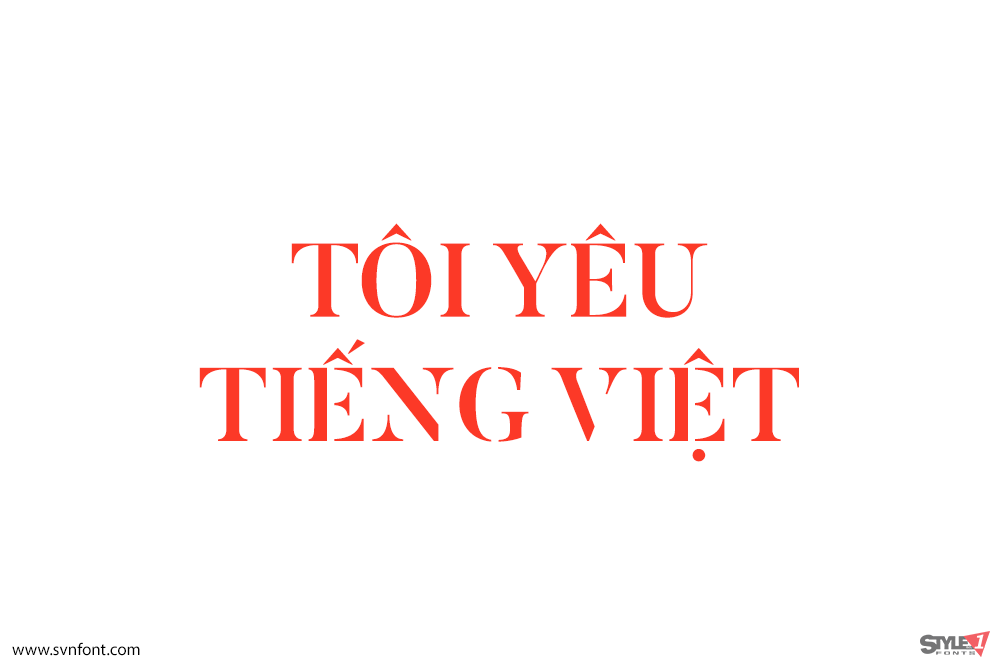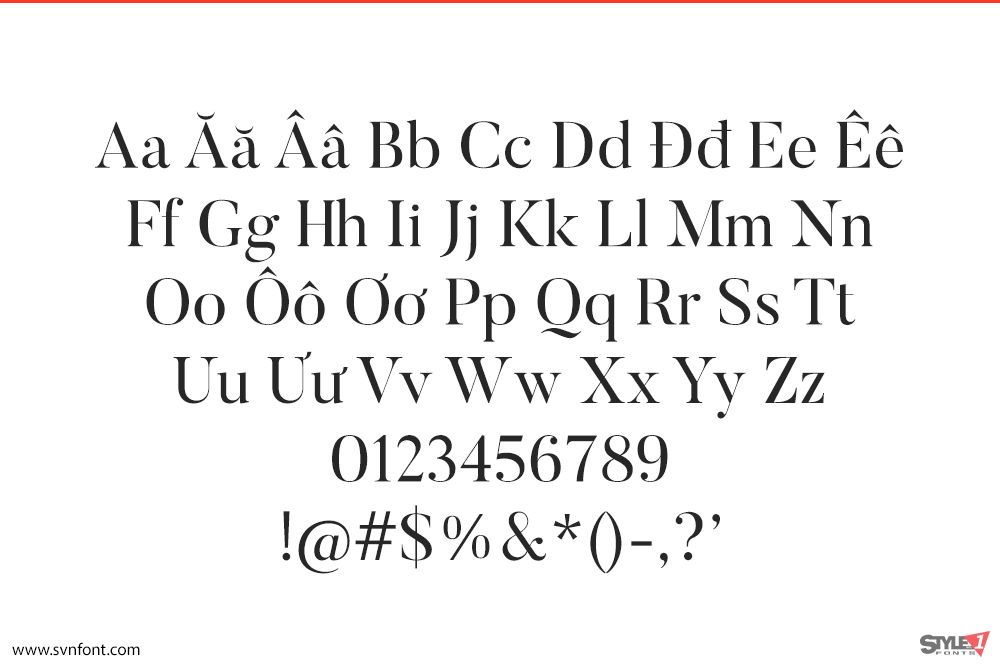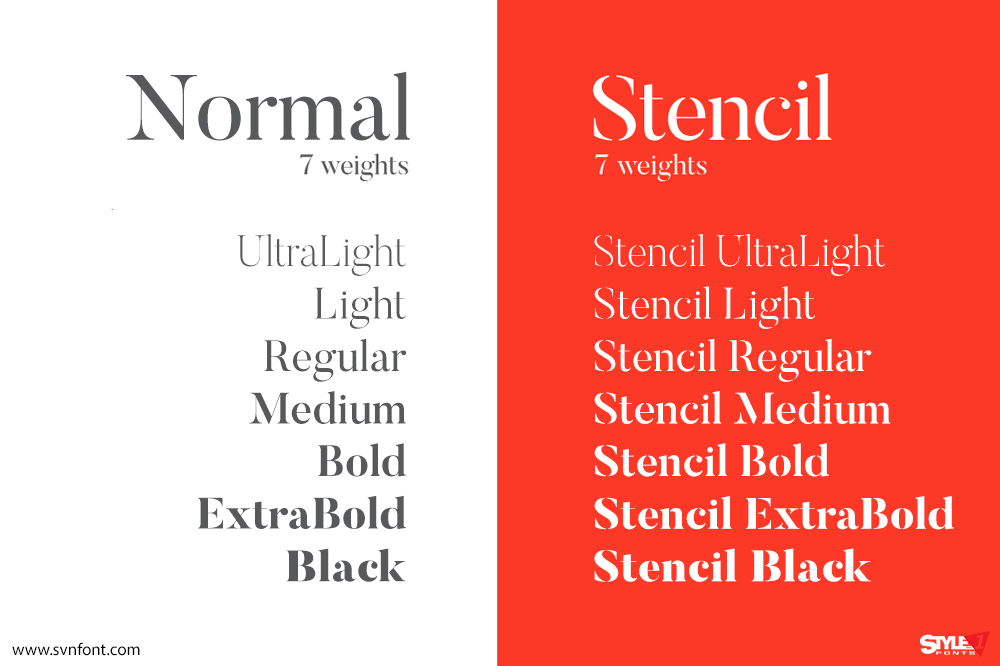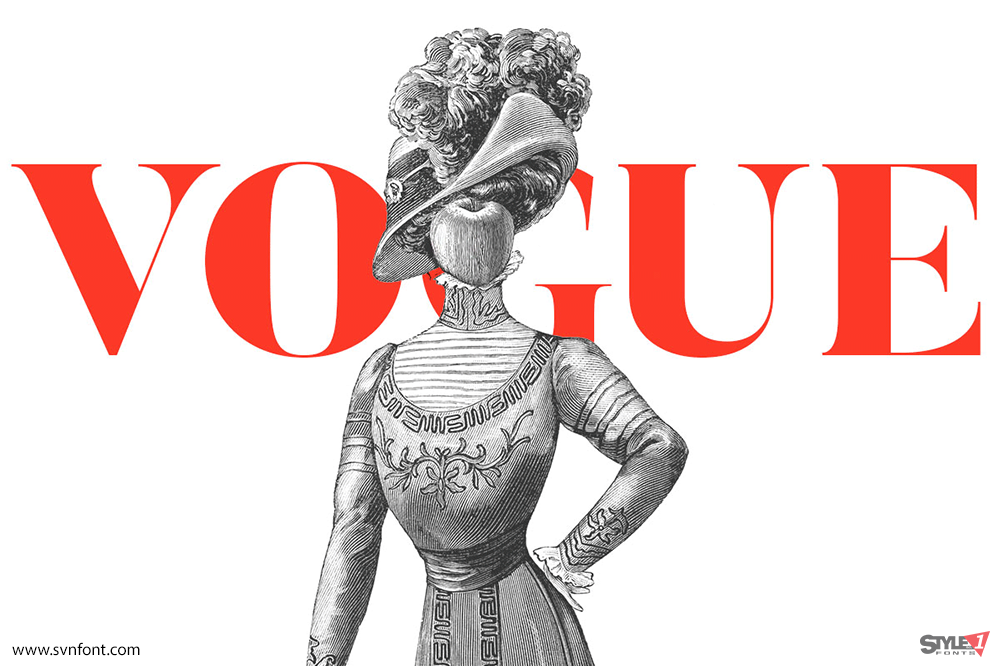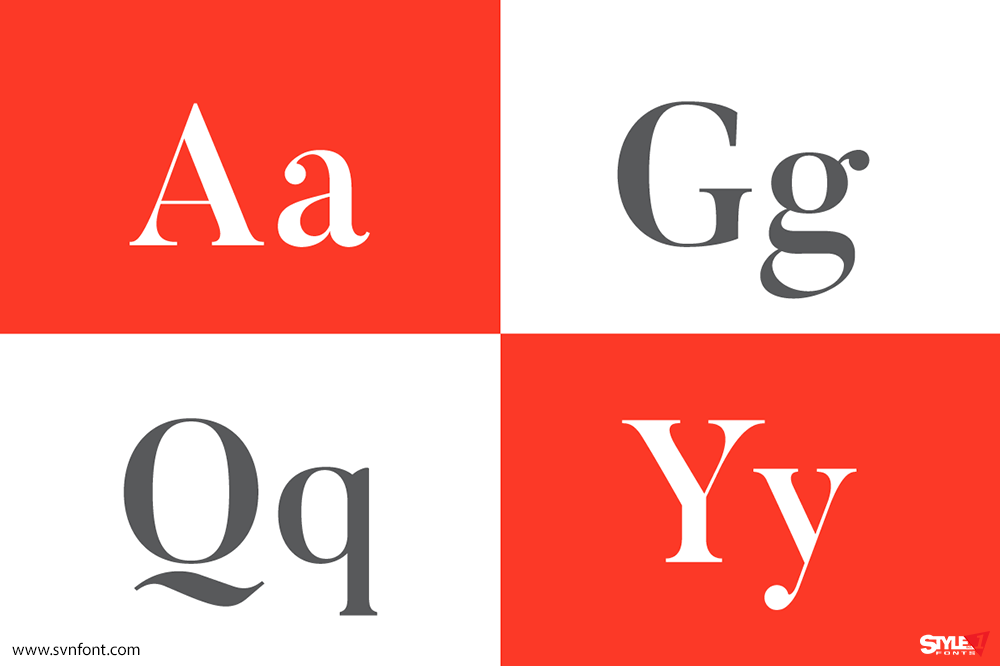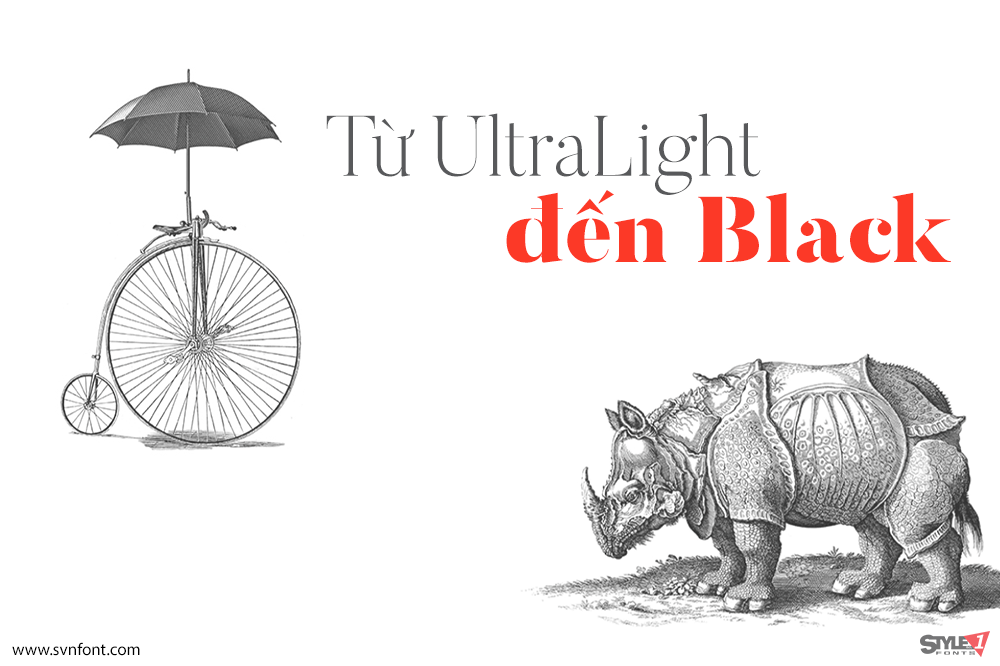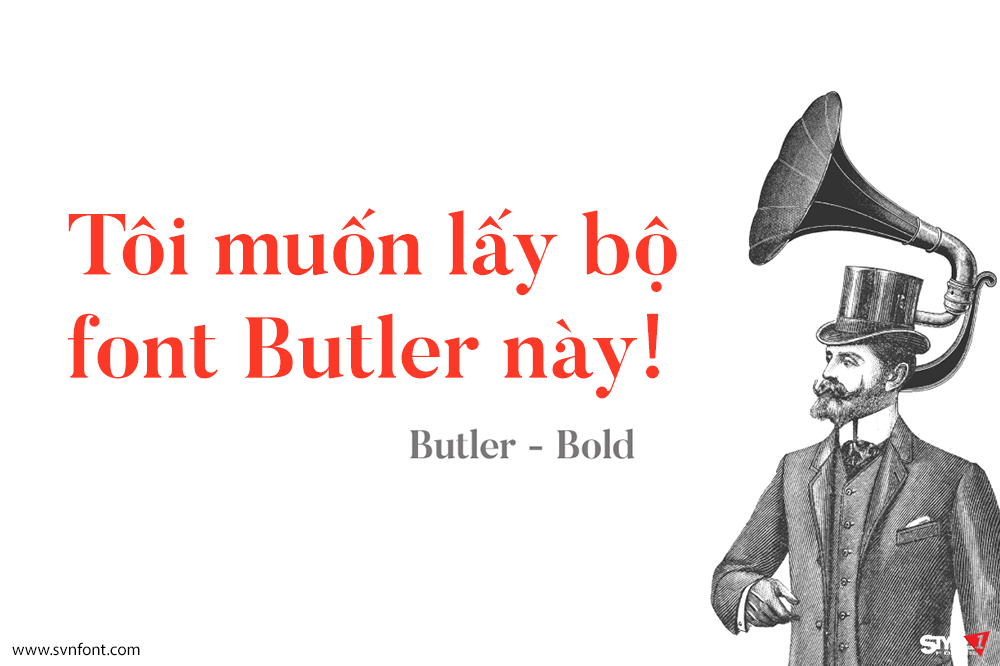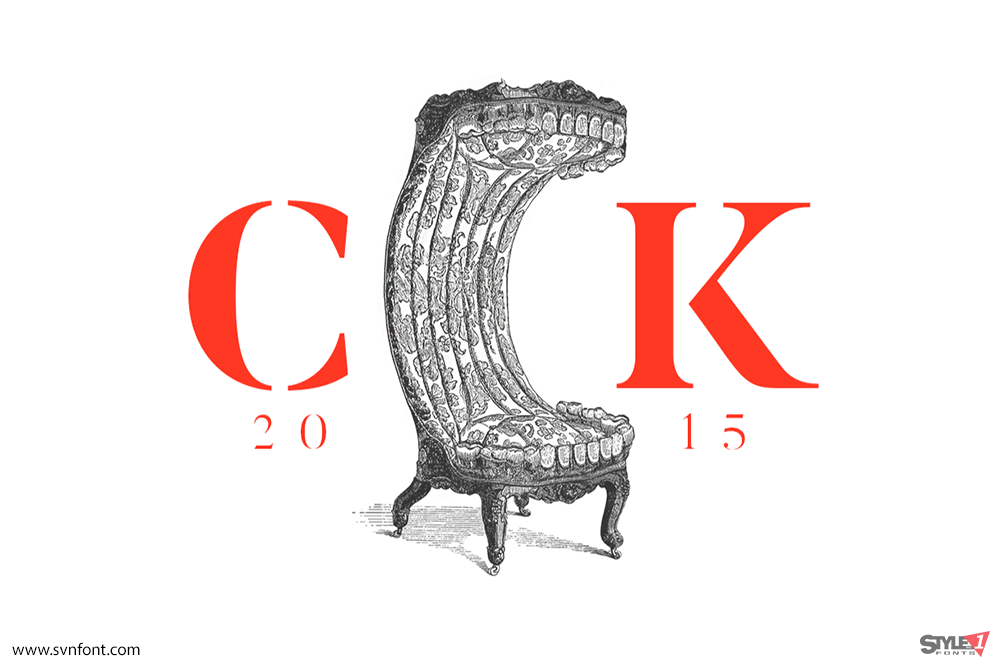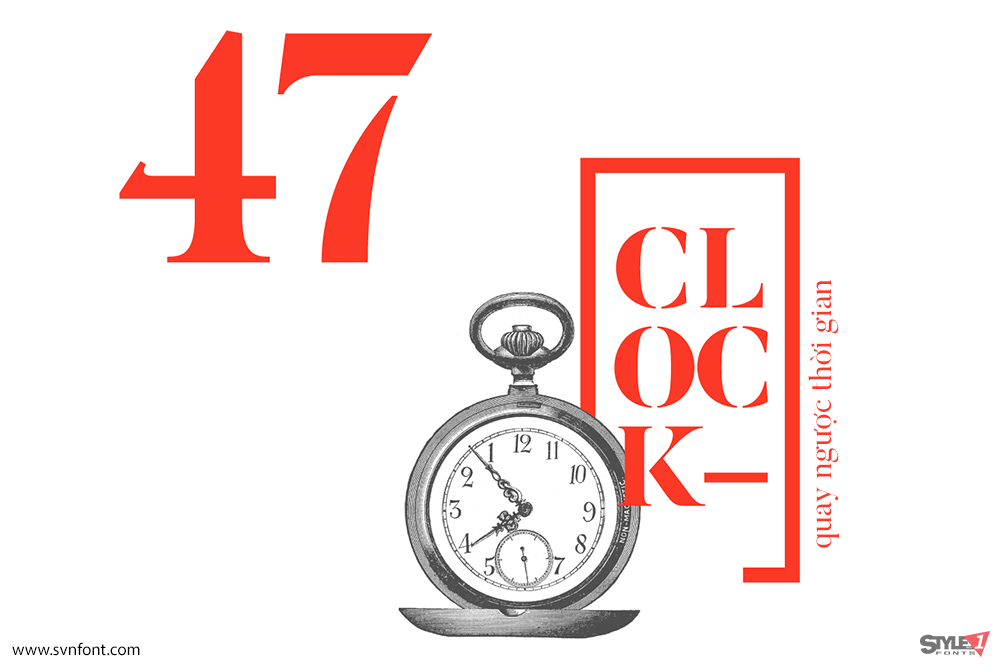
Butler là một font serif miễn phí, được lấy cảm hứng từ sự kết hợp giữa Dala Floda và bộ font Bodoni tuyệt vời. Mục tiêu chính là mang một chút hơi thở hiện đại vào các font serif bằng cách chỉnh sửa các đường cong của những bộ font serif cổ điển và thêm một bộ stencil.
Rất phù hợp cho các poster, tiêu đề rất lớn, sách và những thứ sang trọng, font Butler có độ tương phản cao rất sẵn lòng phục vụ bạn. Bộ Butler tổng cộng có hơn 300 ký tự, 7 độ dày thông thường và 7 độ dày stencil, bao gồm cả số liệu văn bản (text figures), nối chữ (ligatures), phân số và nhiều hơn nữa. Nó cũng hỗ trợ nhiều ngôn ngữ với các ký tự bổ sung.
Nhà thiết kế: Fabian De Smet